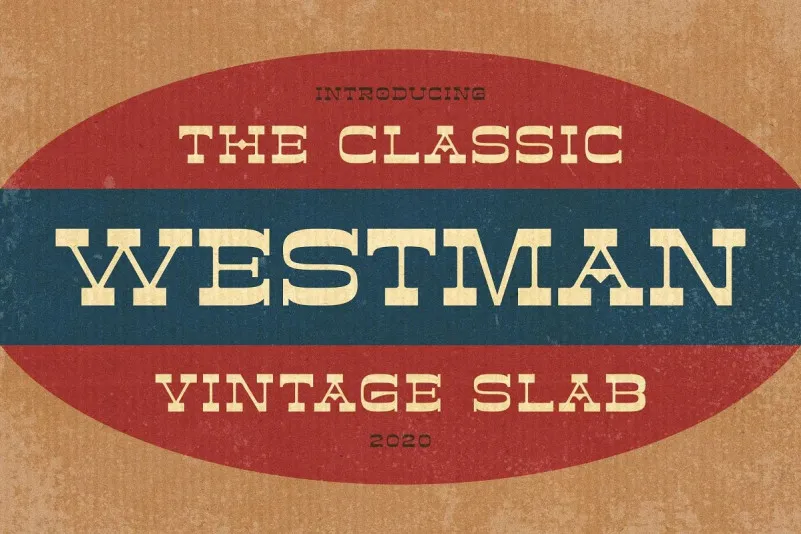
Westman Font
A fonte ‘Westman Font’ é uma elegante mistura de serifada com estilo slab serifado, perfeita para criar logotipos e identidades de marca. Inspirada nos clássicos, mas moderna com nuances retro do início dos anos 60 até os 70, essa fonte traz um toque nostálgico que se tornou uma referência inerente ao design atual. Suas linhas elegantes e suas nuances de estilo slab emolduram o design retro em uma forma que se encaixa perfeitamente no contexto moderno sem perder seu valor histórico, tornando-a uma escolha ideal para designers gráficos buscando um equilíbrio entre a simplicidade clássica e a personalidade vibrante do estilo slab serifa. Este é um recurso visual que se destacará em qualquer projeto de design.